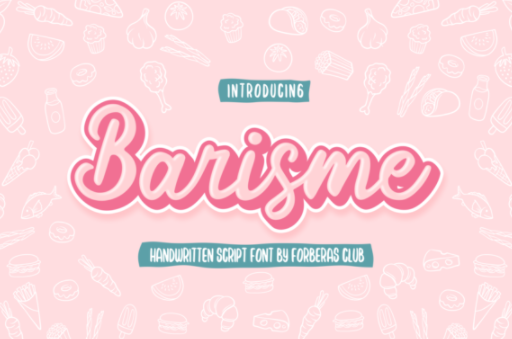
Barsime
- это милый и нежный рукописный шрифт.
Изящный и радостный, этот шрифт идеально подойдет для написания свадебных приглашений, открыток или любого другого дизайна, которому может понадобиться романтический, персонализированный штрих!